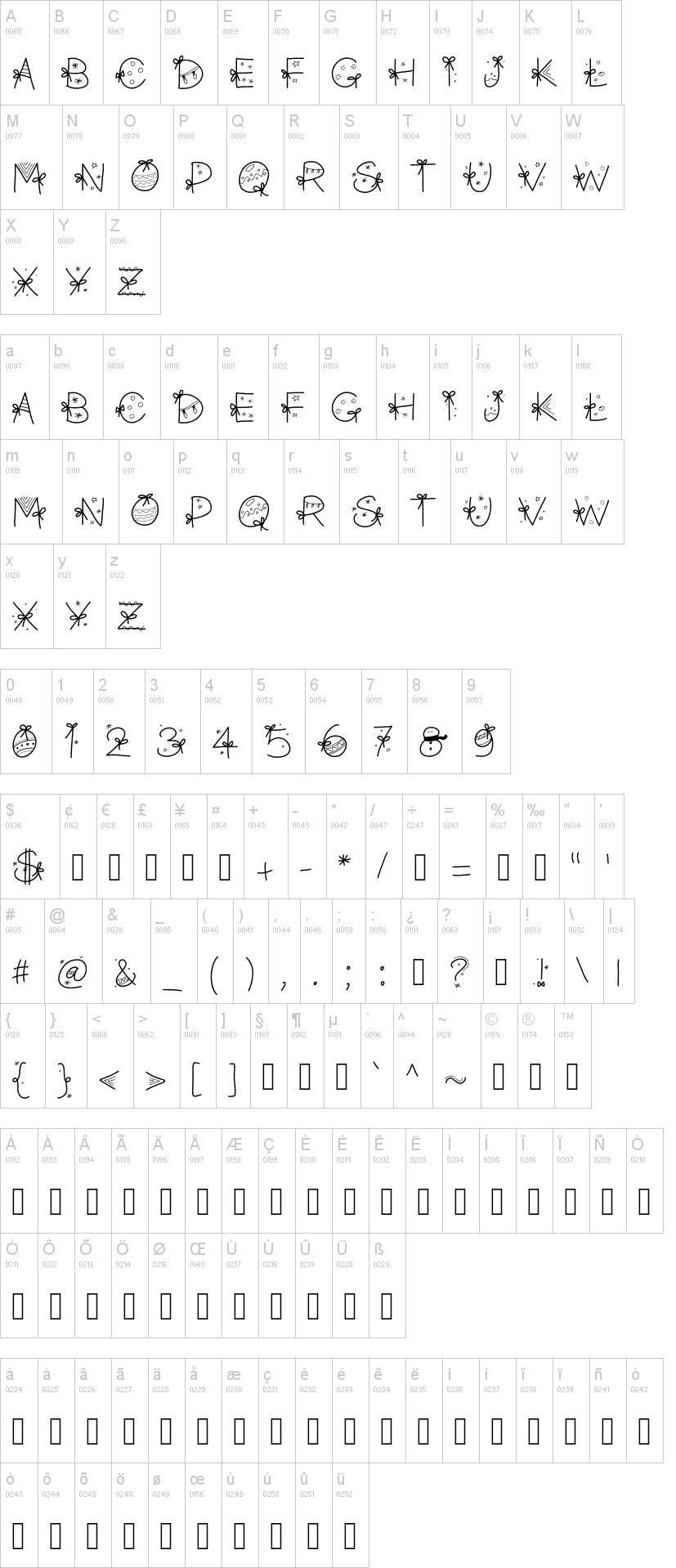
PW Christmas是一種免費的聖誕節主題字體,可以在多種平台上使用,例如Windows、Mac和Linux。它的設計靈感來自於聖誕節的各種元素,如聖誕樹、禮物盒和雪花等。此字體非常適合用於聖誕賀卡、海報、傳單和其他與節日相關的設計項目。 PW Christmas字體有多種字重和样式可供選擇,包括正常、粗體和斜體等,使用戶可以輕鬆地選擇適合自己項目的樣式。在使用時,建議根據需要進行大小和顏色的調整,以確保最佳的顯示效果。內容介紹
PW Christmas是一款非常不錯的手寫藝術字體,具有很好的視覺感,適合於文化類的宣傳設計、商業類品牌的廣告和產品包裝設計以及個性化文字排版等較多場景。